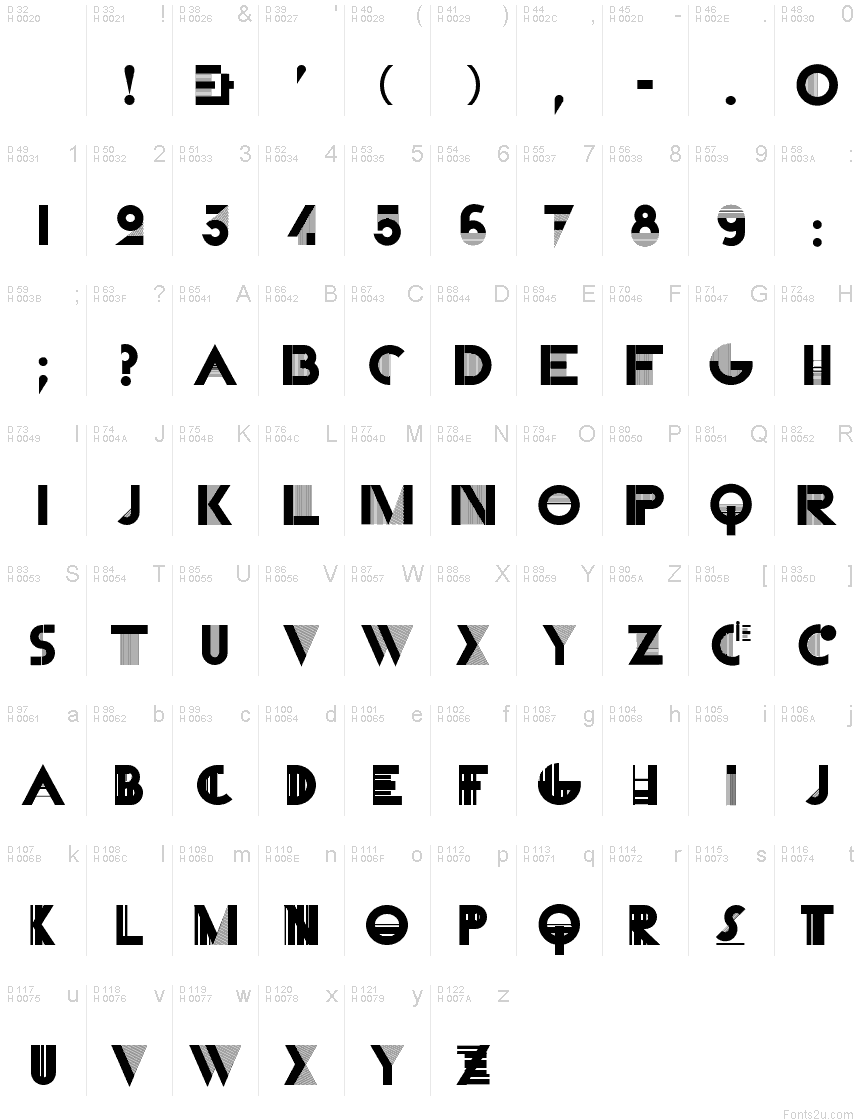
Cassandra Two to darmowy, wyrazisty krój pisma typu display, który łączy głęboką, nasyconą czerń z ostrymi, trójkątnymi cięciami i wypełnieniami w paski. Litery wyglądają, jakby pochodziły prosto z szyldu klubu nocnego z lat 70. – są wysokie, zwarte i pełne graficznych trików, które przyciągają wzrok z daleka. Ciężkie, geometryczne formy, śmiałe kąty i wzorzyste linie nadają krojowi kinetycznego, niemal neonowego blasku zarówno na ekranie, jak i w druku.
Wybierając Cassandra Two, zyskujesz wyrazisty element do plakatów, ulotek rave lub disco, okładek płyt, oprawy wizualnej życia nocnego, grafiki modowej i przykuwających uwagę nagłówków w mediach społecznościowych. Ten bezpłatny font najlepiej sprawdza się w dużych rozmiarach, gdzie jego detale w paski i masywne sylwetki mogą w pełni zaistnieć. Zestaw go z prostym, dyskretnym krojem bezszeryfowym w tekście głównym i pozostaw nieco większe światło między literami, aby każda wyrzeźbiona forma mogła się wyróżnić.